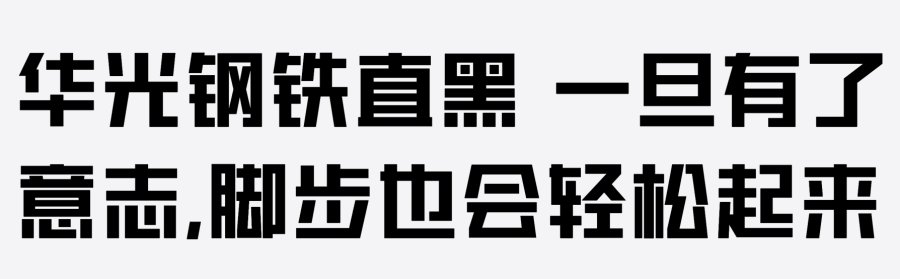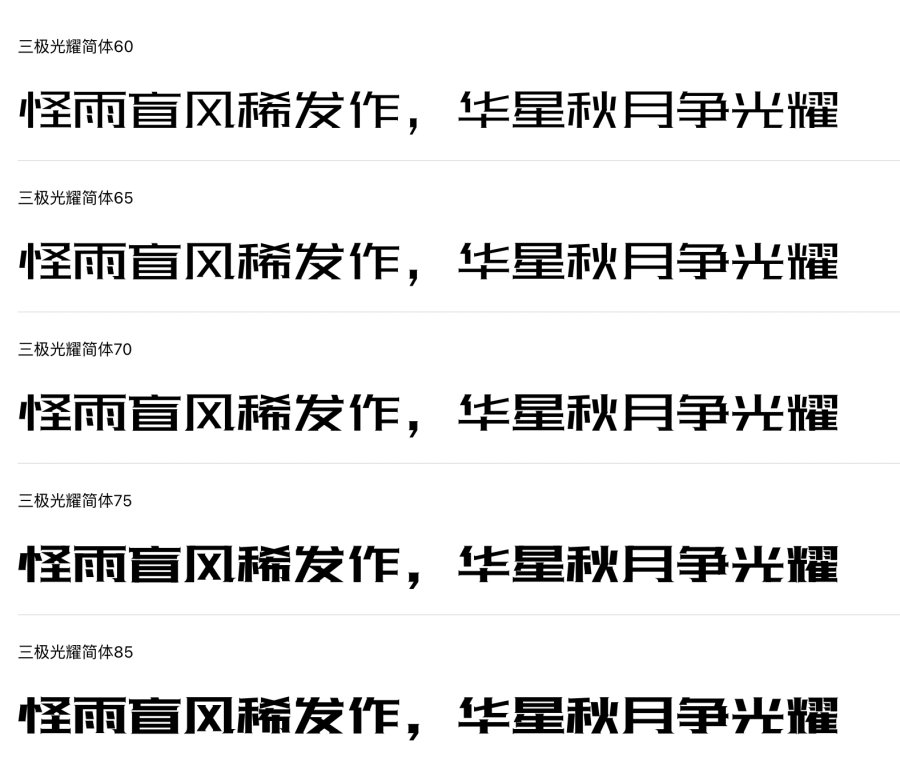
上首壹方体风格端庄严谨,笔画粗壮浑厚,整体特征坚硬、有力。具有现代、国际化的指向性。
上首壹方体
华光钢铁直黑 精平直的笔画,规整的线条,扎实的结构,方正的字形,此套字体表现出刚正不阿、一丝不苟的品质。适用于广告杂志、标题标语、影视包装网页设计等场景。
华光钢铁直黑 精
三极光耀简体是一款非常有个性的系列字体,采用大字面,横细竖粗,显得字形稳定扎实。整个字体以方形为结体,彰显大气且明快有力。每个字棱角分明,锋芒毕露。在字体的结构上采用了一些建筑的元素,具有建筑造型之感,突显字体的大气蓬勃之势,其丰富的艺术形象,大大的加强了审美效果。
三极光耀简体系列字体展示